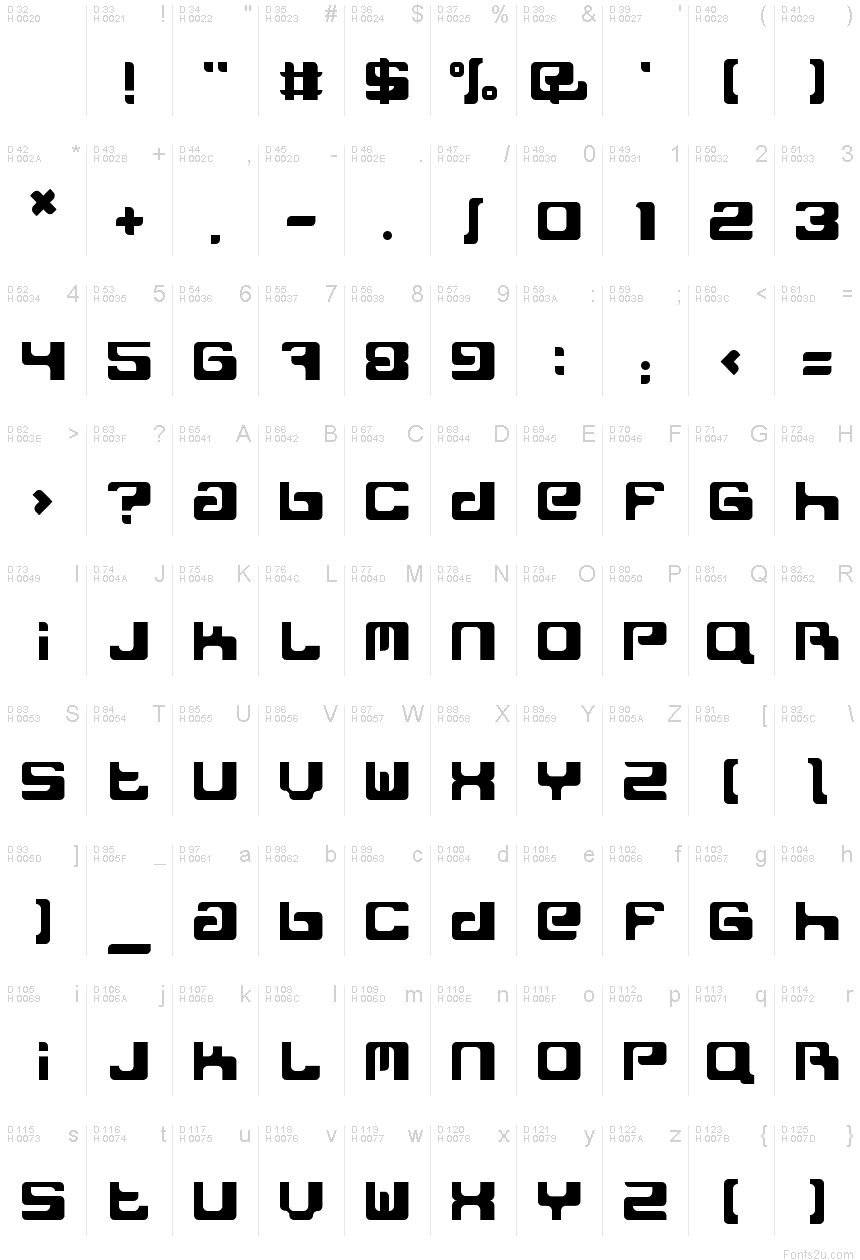
Freak, di Michaël Pinto, è un carattere display gratuito e groovy con curve spesse e squadrate, come se fossero state versate in una griglia e poi leggermente spostate. I tratti massicci e monolitici, uniti a spazi interni stretti e scolpiti, conferiscono a ogni parola un ritmo audace e sintetico, un mix tra un cabinato arcade e un flyer da club underground. Le lettere si incastrano come tessere lucide, creando una silhouette pesante e compatta che cattura l'attenzione fin dal primo sguardo.
Usando Freak, i titoli acquisiscono subito un'energia notturna e coinvolgente, perfetta per poster musicali, identità visive per club, flyer di festival, loghi streetwear, fanzine e grafiche social d'impatto. Questo font gratuito dà il meglio di sé nei grandi formati, dove le sue forme squadrate possono respirare; abbinalo a un sans serif geometrico pulito per il testo principale per mantenere layout nitidi e leggibili.